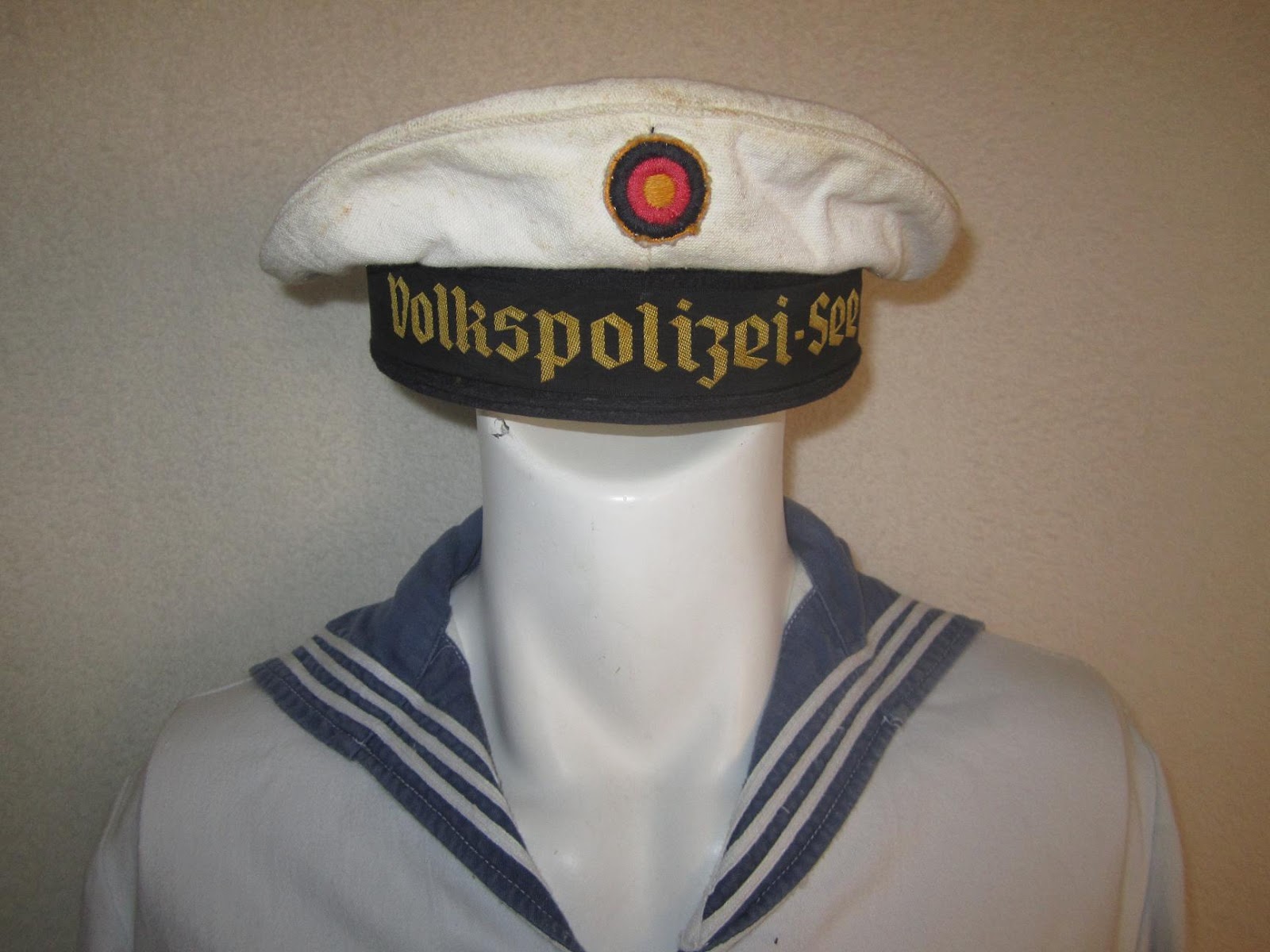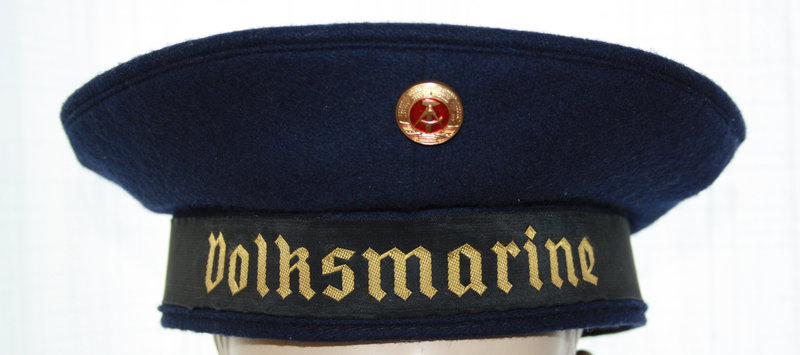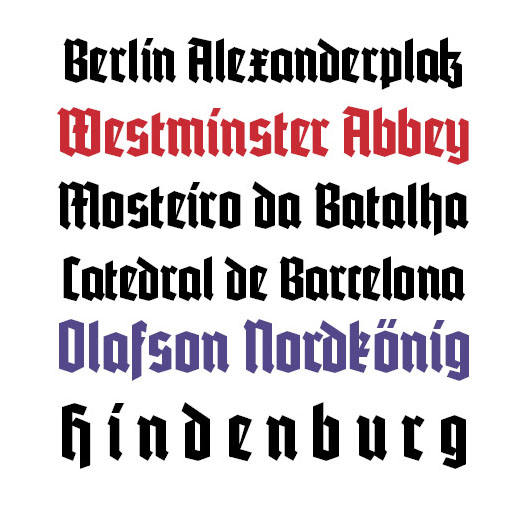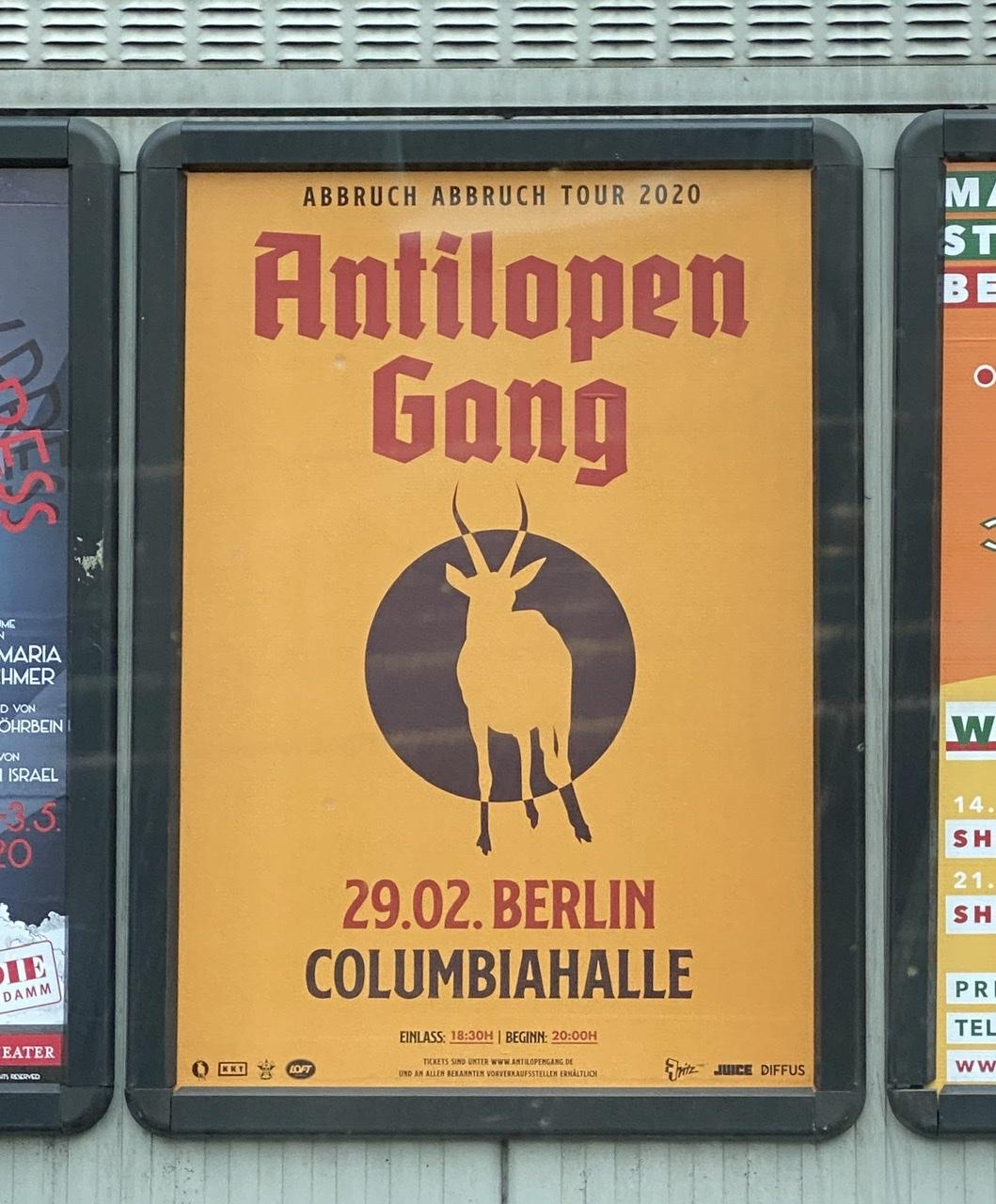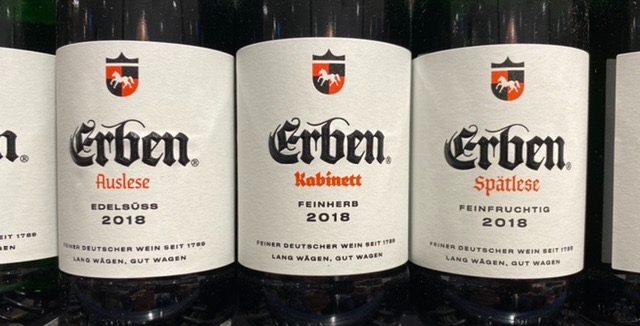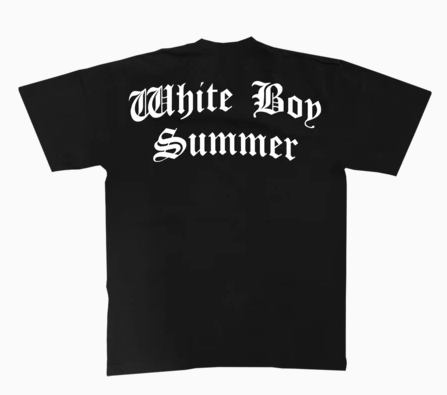
Schaftstiefelgrotesk?
Na ja, es ist halt, gemessen an ihrem kontroversen Status, die ultimative Schriftgattung. Von daher stimmt’s dann vielleicht wieder irgendwie?
Hatten wir die eigentlich schon?
Ich kann da nichts Militärisches oder Nazihaftes erkennen, wenn man ausblendet, dass Fraktur oder Gotisch gerne verwendet wird, um Nazis zu symbolisieren, und dadurch erst im Nachhnein ein falsches Bild entstanden ist.
Interessanterweise war Adolf Hitler selbst als ehemaliger Kunstmaler gar kein Anhänger der Fraktur oder Gotisch oder Gebrochenen Schriften. Er war ein Freund der Antiqua, sogar der damals so titulierten Grotesken.
Im Detail nachzulesen ist das im Handbuch der Frakturschriften von Wolfgang Hendlmeier aus München, erschienen im Delbanco-Verlag. Hier eine Besprechung aus eigener Feder:
Keine Ahnung ob die Welt darauf gewartet hat - bin nur gerade darüber gestolpert: Golpon
Die Golpon ist eine Display-Fraktur. Sie wurde inspiriert von anderen geometrischen Frakturen wie die Potsdam, oder die Kaas von d’Alte, oder Max Bittrof’s Element [1933].
im pdf findet sich übrigens ein schönes Zitat von Friedrich Genzsch aus dem Jahre 1928
„Es wäre ... ein ebenso falsches wie vergebliches Bemühen, wenn wir für unsere Gegenwart und Zukunft irgendeinen der historischen Stile festhalten oder neu beleben wollten. Folgerichtig drängt die Entwicklung unserer Maschinentechnik nach einfachsten Gestaltungen und klarsten Ausdrucksformen.“
welchen auch meine Vermutungen mit dem Bauhaus oder sagen wir "Elementaren Typografie" unterstreicht.
weiter:
ein Werbetext von 1934 lobt die Vorzüge der Type Element: „Ele-ment – Die klare deutsche Schrift der neuen Typographie. Die deutsche Schrift lebt fort als der sichtbare Ausdruck deutschen Wesens. Sie gehört nicht der Vergangenheit an. Und deshalb haben wir die Verpf lichtung, mehr zu tun, als Formen der Vergangenheit abzuwan-deln und zu wiederholen.“
Und deshalb haben wir die Verpf lichtung, mehr zu tun, als Formen der Vergangenheit abzuwan-deln und zu wiederholen.“
Da bräucht ich jetzt ein bischen Nachhilfe: was wär denn die Element anderes als eben ein „ abzuwan-deln“  bestehender Formen. Ist doch im Endeffekt jede neu entworfene Schrift. Um so mehr, wenn sie sich „als sichtbare(n) Ausdruck deutschen Wesens“ versteht.
daß diese Schriften nie wieder salonfähig werden.
sind sie doch bereits, sie werden ja weiterhin verwendet, wenn auch nicht mehr so oft wie in den 30ern.
das antilopen-gang-plakat ist ein schönes beispiel um zu zeigen wie man den nazis ihre symbole wegnehmen und umdeuten kann. siehe auch: http://rechtsgegenrechts.de
Gerade im »Guardian« (und bestimmt auch anderswo: »Tom Hanks’s son criticized for using ‘racist’ font on merchandise collection.«
Und so sieht's aus:
Weiß jetzt so gar nichts über den Sohn von Tom Hanks. Aber diese Botschaft mit dieser Schrift kommuniziert hat halt auf den ersten Blick  eindeutige Aussagekraft. Kann jetzt Blödheit sein, oder Absicht, oder Provokation. Aber wenn nicht Absicht, dann gehört es eben auch aufgelöst.
Das liegt aber doch an der Botschaft, nicht an der Schrift.
Mag jetzt ob mangelnder Informationen darüber niemandem was unterstellen. Aber auf den ersten Blick wirkt eben die Schrift nicht zufällig gewählt.
Ja, Schrift wirkt.
Nun, die Schrift als solche ist natürlich nicht rassistisch. Sie ist ein Werkzeug, dass neben dem Informationsgehalt durch die Form an sich und durch die Laute, die sie repräsentiert, aber auch Emotionen transportiert. Hätte der Designer polymeraſe chain reaction oder Wurſtwaſſer so aufs Shirt gedruckt, hätte da wohl kein Hahn nach gekräht.
Aber ich glaube nicht, dass hier die gleiche Situation vorliergt wie es in Deutschland wäre mit seinem Anklange von Nazi-Zeit. Die USA haben eine andere Bindung zu Gebrochenen. Ich bin kein Spezialist für US-Volksempfinden, doch scheint mir die Akzeptanz von gebrochenen Schriften dort viel höher, denn sie vermitteln ein Gefühl, das mehr in Richtung "gute alte Zeit" und "früher war alles besser" geht. Dieses T-Shirt jedoch impliziert da für mich die Zeit wenigstens der Rassentrennung, wenn nicht gar die Zeit der Sklaverei.
Sobald ich übrigens in die Artikel hineinschaue, finde ich übrigens bemerkenswerte Differenzierungen (von mir unten gefettet), stellvertretend zitiere ich mal msn:
His black and white range of clothes, which include hoodies, T-shirts, shorts, tank tops, leggings, caps and bike shorts, has been called out online for its use of a Gothic-style font that is close to the one used by white nationalists. It’s also similar to the Fraktur font, which was used in Nazi German most prominently on the cover of Hitler’s Mein Kampf book.
aufdrängen
Das tut doch keiner?!
Und zum "halbwegs passen": Also ich designe meine persönliche Korrespondenz nicht durch, da verwende ich die Schriften, die ich mag und die beim Adressaten nicht gleich Brechreiz auslösen. Und das kann gerne mal eine gebrochene Schrift sein (s. meine Lieblingsschriftenliste)